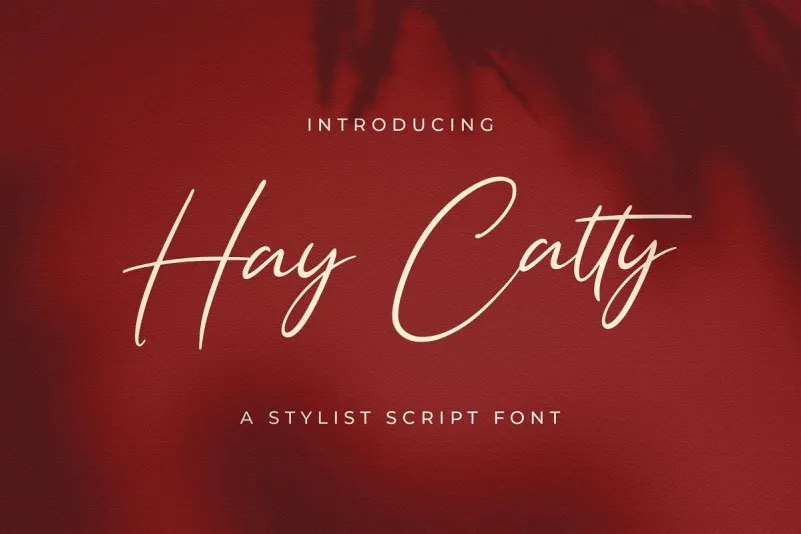
A Hay Catty Script Font é uma fonte escrita a mão com um toque delicado que transmite um encanto natural. Manufacturada pela StringLabs, esta fonte é simples, mas sua influência visual é forte e inegável. Ela pode ser usada em uma variedade de aplicações, seja em design gráfico ou até mesmo em criações digitais. Com a Hay Catty Script Font, suas ideias criativas ganham vida quando são projetadas com essa fonte. Seja para adicionar um toque pessoal em seu logo ou até para dar um ar único e especial aos textos de apresentação da sua marca, esta fonte manuscrita é perfeita. A Hay Catty Script Font é uma opção ideal tanto para profissionais que buscam um recurso gráfico sofisticado quanto para iniciantes apaixonados por design.